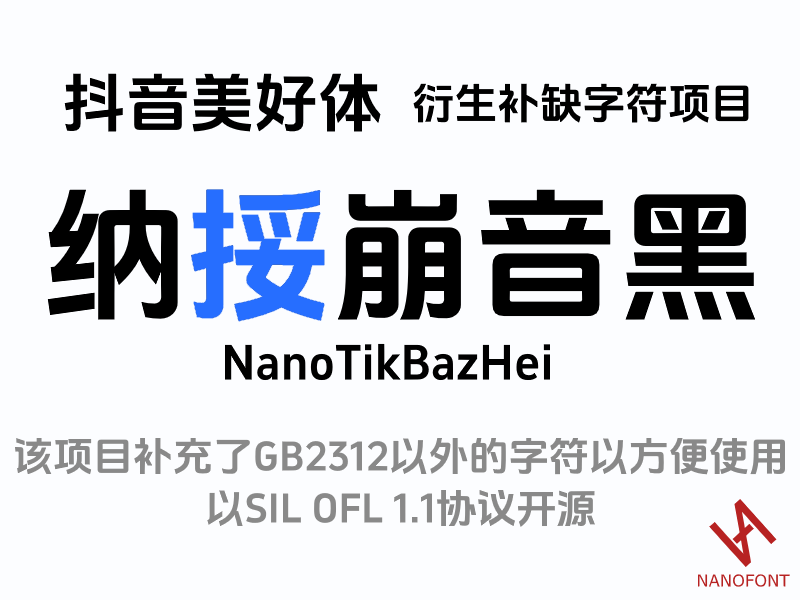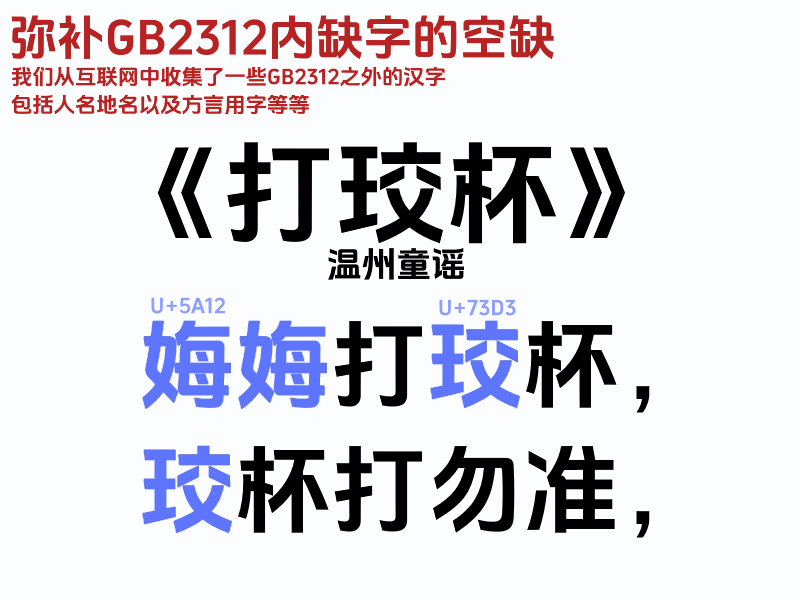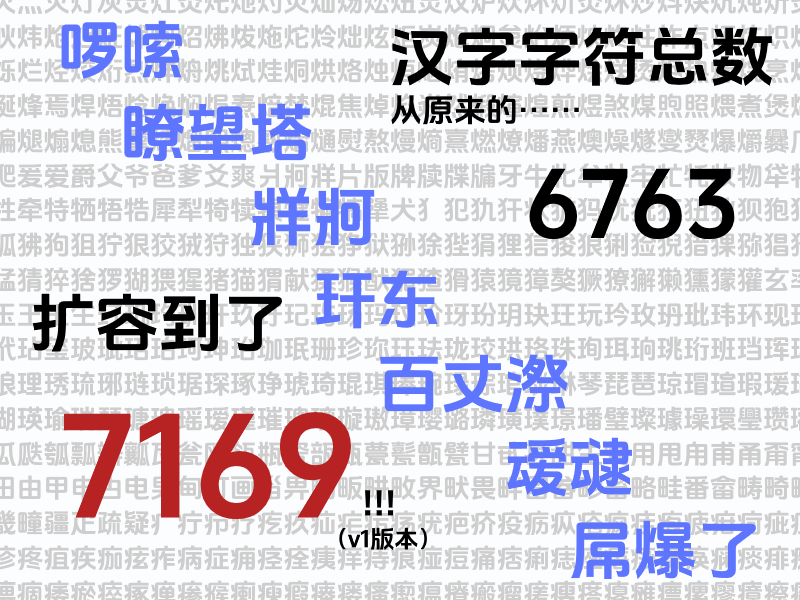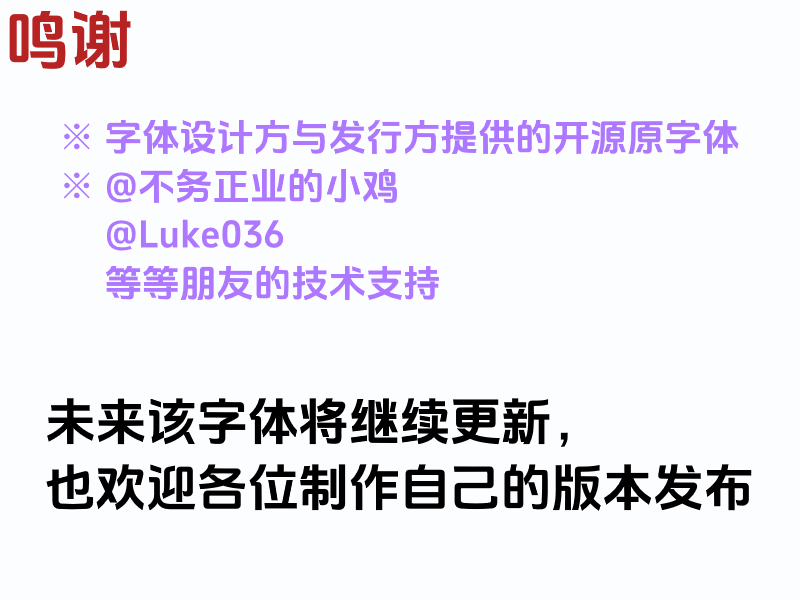
纳挼崩音黑
纳挼崩音黑(NanoTikBazHei)是一款由纳挼字库制作的中文黑体衍生字体,字体以抖音美好体为基础进行字符扩展,在延续原字体简洁、现代的黑体视觉风格的同时,针对实际使用过程中存在的缺字问题进行了补充。整体字形端正利落,笔画简洁醒目,具有较强的视觉识别度,适合用于海报标题、短视频字幕、社交媒体配图以及各类中文视觉设计。
纳挼崩音黑:抖音美好体衍生补字开源字体
纳挼崩音黑的设计思路并非重新塑造一种完全不同的字体风格,而是在原有字形基础上进一步完善中文字符覆盖。抖音美好体原版主要支持 GB2312 字符集,在实际输入一些人名、地名以及特殊汉字时,偶尔会出现无法显示的情况。针对这一使用痛点,纳挼字库对 GB2312 之外的部分汉字进行了收集与补充,让字体在面对更加复杂的中文文本时拥有更好的适应能力。
纳挼崩音黑:抖音美好体衍生补字开源字体
在字形表现上,纳挼崩音黑延续了现代黑体简洁直接的特点。字体整体结构清晰,笔画具有较好的统一性,横竖笔画之间保持着稳定的视觉秩序,字面表现醒目而不繁琐。较为规整的结构使其在大字号排版中具有不错的视觉冲击力,同时也能够保持较好的文字辨识度,适合强调信息传达与视觉表现的设计场景。
纳挼崩音黑:抖音美好体衍生补字开源字体
此次字符扩展也是纳挼崩音黑较为明显的特点之一。字体在原有约 6763 个汉字的基础上进一步增加字符,总汉字数量扩展至约 7169 个,补充内容主要涵盖部分 GB2312 之外的人名用字、地名用字以及方言用字等。虽然扩展的字符数量并非庞大的完整汉字字库,但能够针对日常文字使用中容易遇到的特殊字符进行补充,从而减少排版过程中因为缺字而更换字体的情况。
纳挼崩音黑:抖音美好体衍生补字开源字体
视觉风格方面,纳挼崩音黑拥有较为鲜明的现代感与数字感。黑体本身简洁、清晰的特点,使它能够很好地适应互联网内容和现代视觉设计,同时又不会因为装饰性过强而限制使用场景。用于标题时能够形成干净有力的文字效果,用于字幕和配图文字时也能够保持良好的阅读体验。
在应用方面,纳挼崩音黑适合用于短视频字幕、宣传海报、活动物料、社交媒体图片、品牌宣传、网页标题以及日常平面设计等场景。尤其是在需要使用特殊人名、地名或扩展汉字的设计中,更丰富的字符支持能够让字体拥有更加完整的使用体验。
纳挼崩音黑:抖音美好体衍生补字开源字体
总体而言,纳挼崩音黑是一款以“延续原有风格+扩充中文字符”为核心思路的黑体衍生字体。它没有刻意改变原字体简洁现代的视觉特征,而是从实际使用需求出发,对容易出现缺字的部分进行补充,让熟悉这类黑体风格的设计师和创作者能够在更多中文内容中保持统一的字体表现。